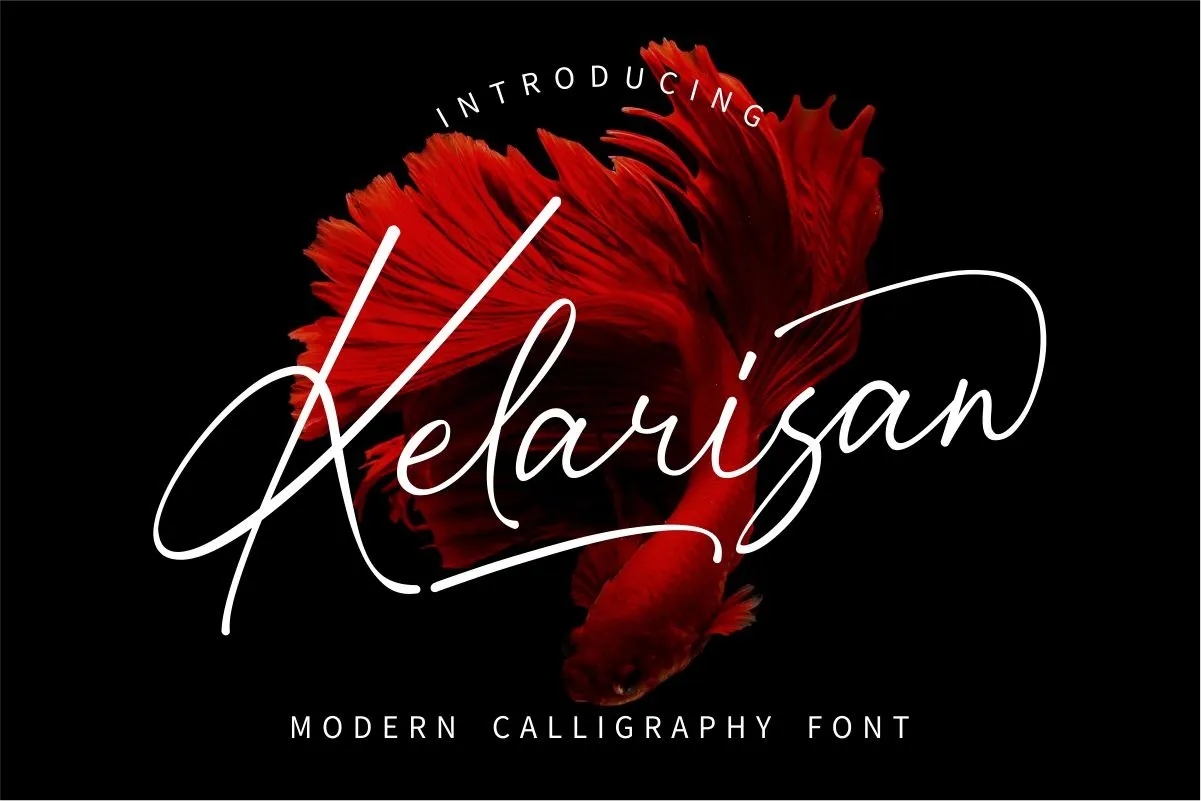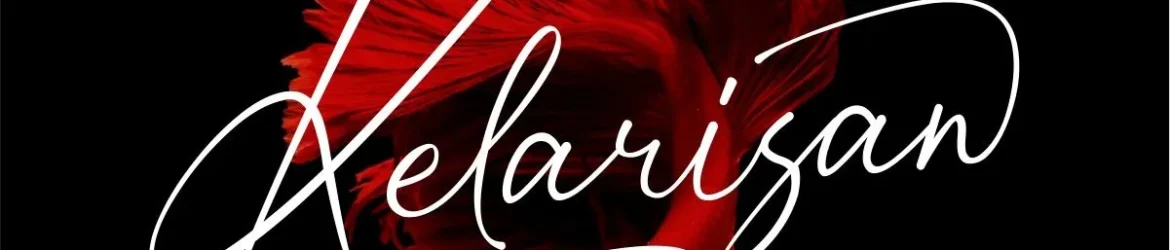
A fonte “Kelarisan Font” é uma elegante mistura de moderna calligrafia criada pela GFRcreative. Com seu estilo casual e suavemente charmoso, esta fonte apresenta desenhos finos que se assemelham a pontas de caneta suaves. Ideal tanto para textos sem compromisso quanto para trabalhos mais formais, Kelarisan é perfeita para projetos atuais e futuros. Suavemente delicada com detalhes elaborados, ela oferece um toque refinado que enriquece qualquer design que você desenhe. Combinada com outros recursos de design, essa fonte traz um toque único aos seus trabalhos gráficos.